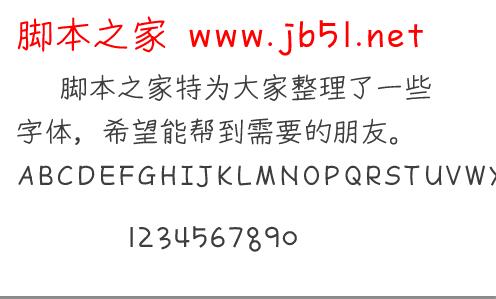
和睦雨沫體字體是一款書(shū)寫(xiě)非常新穎的中文字體,該字體不甚工整,多處在轉(zhuǎn)折處進(jìn)行了處理,使得字里行間多了些趣味,一點(diǎn)也不死板,整體看上去有一種如沐春風(fēng)般的感覺(jué),可以很好的應(yīng)用于文本裝潢、信息展示、網(wǎng)頁(yè)設(shè)計(jì)、篆刻制模、數(shù)據(jù)制作、裝潢設(shè)計(jì)、計(jì)算藝術(shù)設(shè)計(jì)、視覺(jué)設(shè)計(jì)、字帖等一切合法應(yīng)用場(chǎng)景,有喜歡的朋友可免費(fèi)下載收藏。